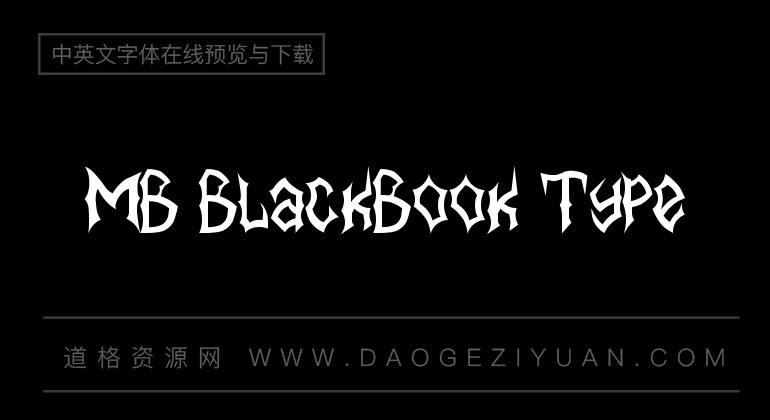
MB BlackBook Type 字体是一种现代风格的手写字体,它的特点是具有粗犷、有力、直接的效果。这种字体在设计中常用于突出重要信息、强调主题和增强视觉冲击力。MB BlackBook Type 字体的字形笔画宽度不均匀,有时笔画粗细交错,增加了字体的动感和生命力。此外,它的字母形状也比较独特,有时候会具有一些角度或者有点偏斜。总体来说,MB BlackBook Type 字体是一种非常醒目、具有强烈个性的字体,适用于各种场合的设计。内容介绍
MB BlackBook Type是一款非常不错的手写艺术字体,具有很好的视觉感,适合于文化类的宣传设计、商业类品牌的广告和产品包装设计以及个性化文字排版等较多场景。